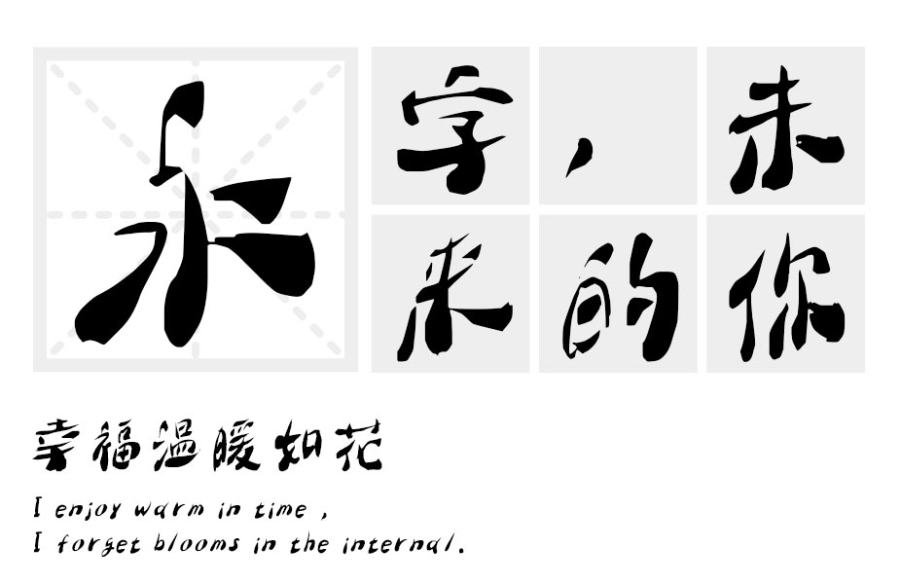
大梁电脑合成体发布
字体名称:大梁电脑合成体
字体类别: 创意字体
适用场景:广告、屏显、动漫、影视
大梁电脑合成体简介:利用软件技术生成的著名书法家大梁(北京徐悲鸿纪念馆主任)的一套字库,尝试软件和书法家毛笔书写配合,*终笔画具有独具风格特点,具有独具特色的书法意境。
大梁电脑合成体预览图展示: